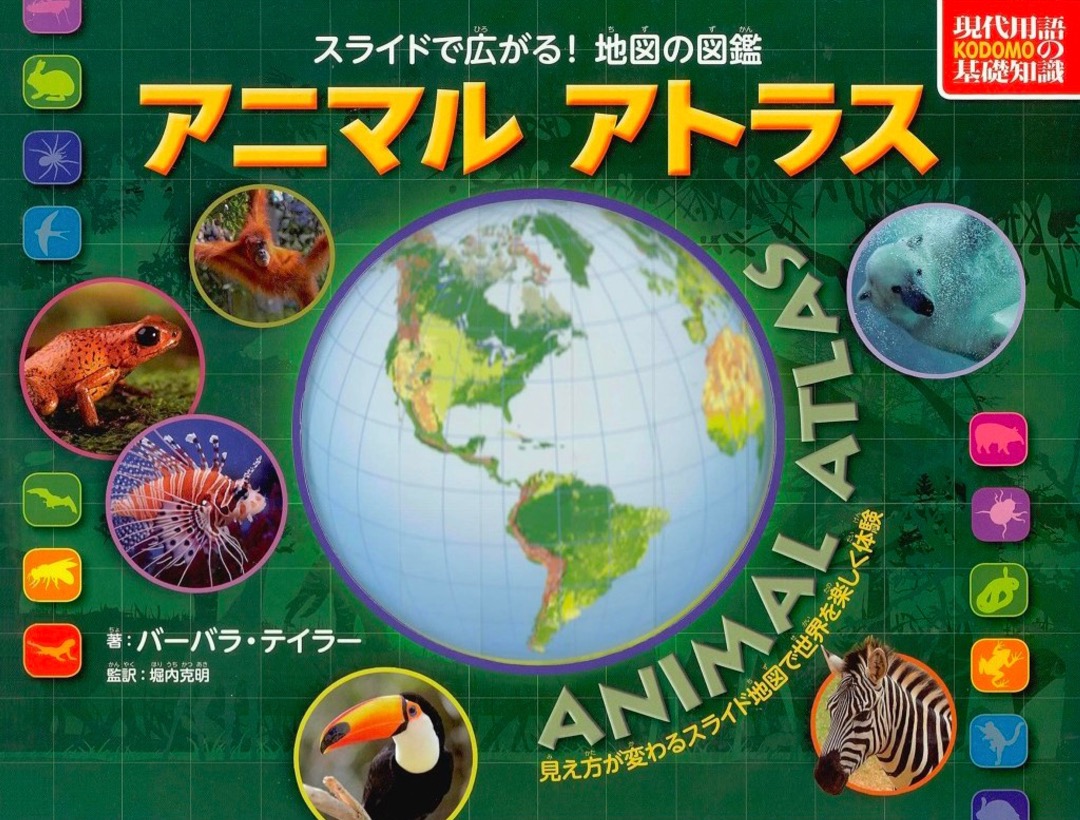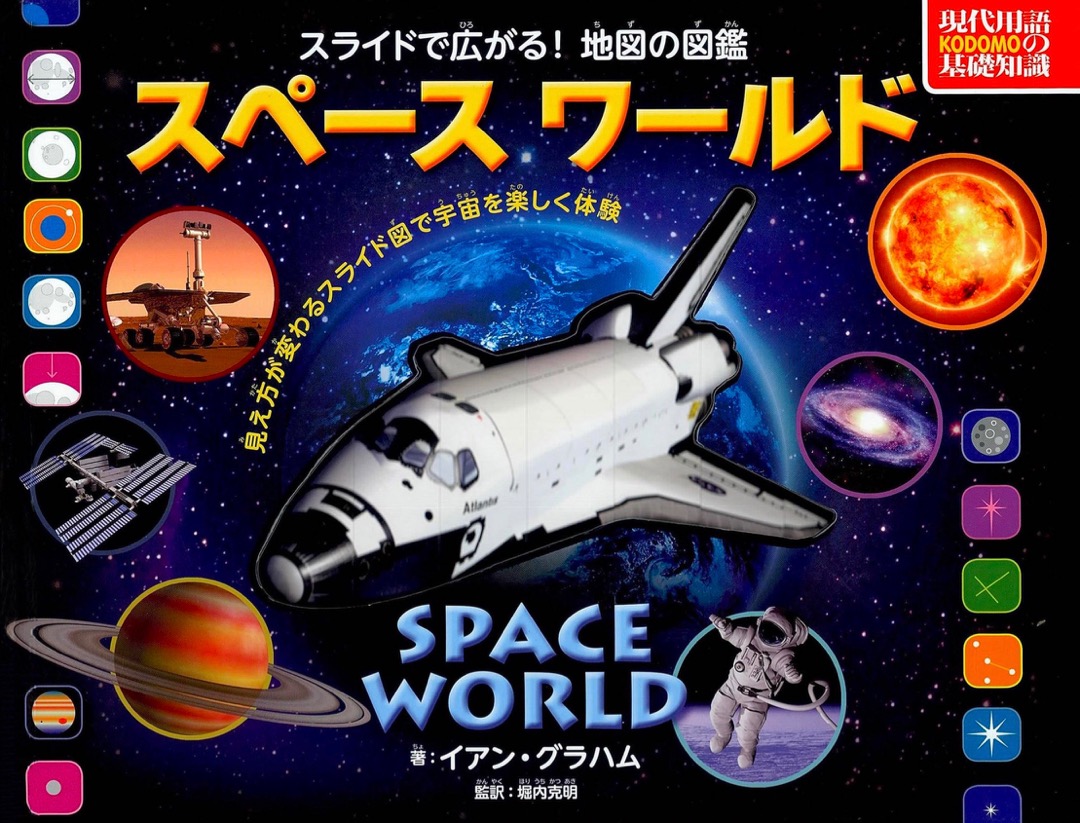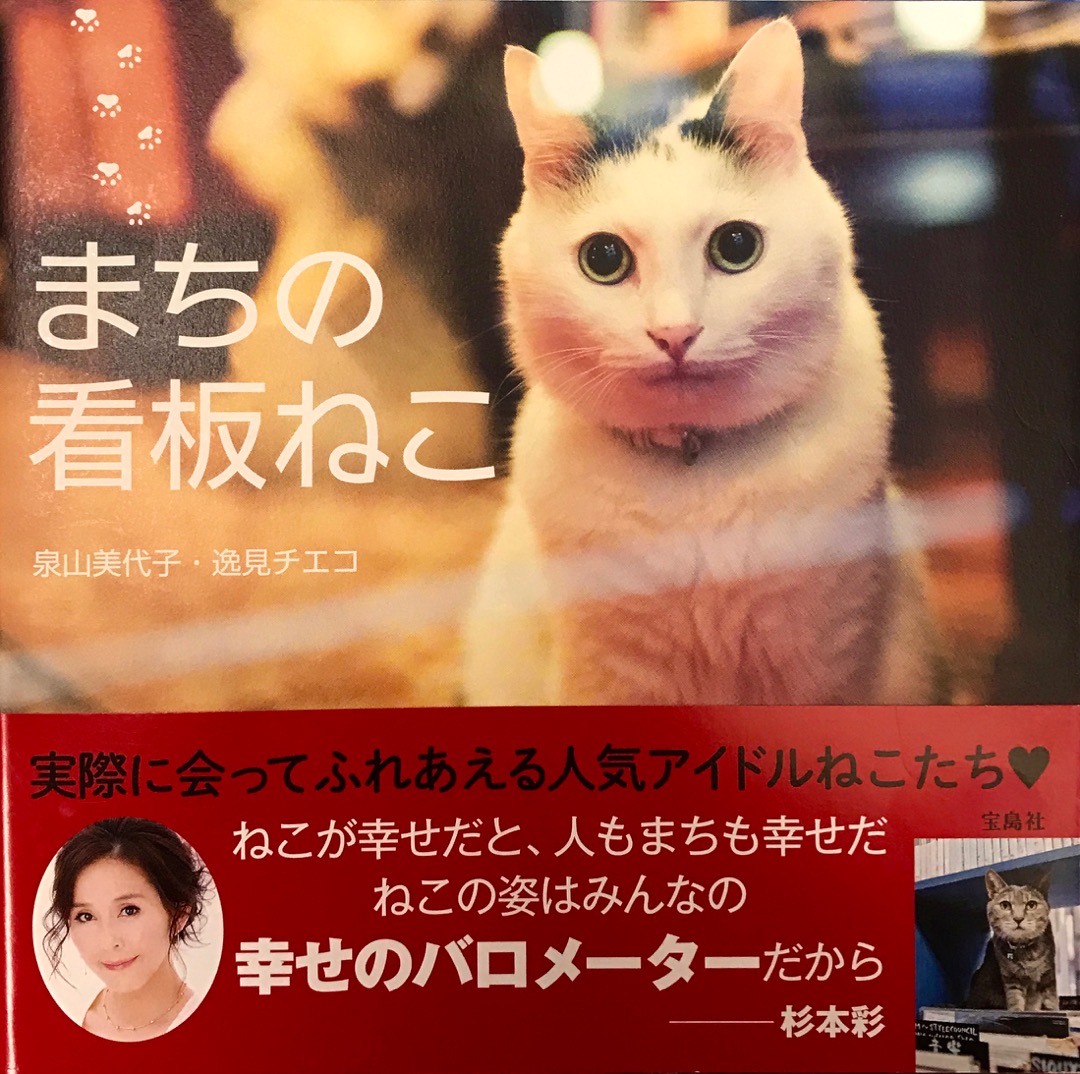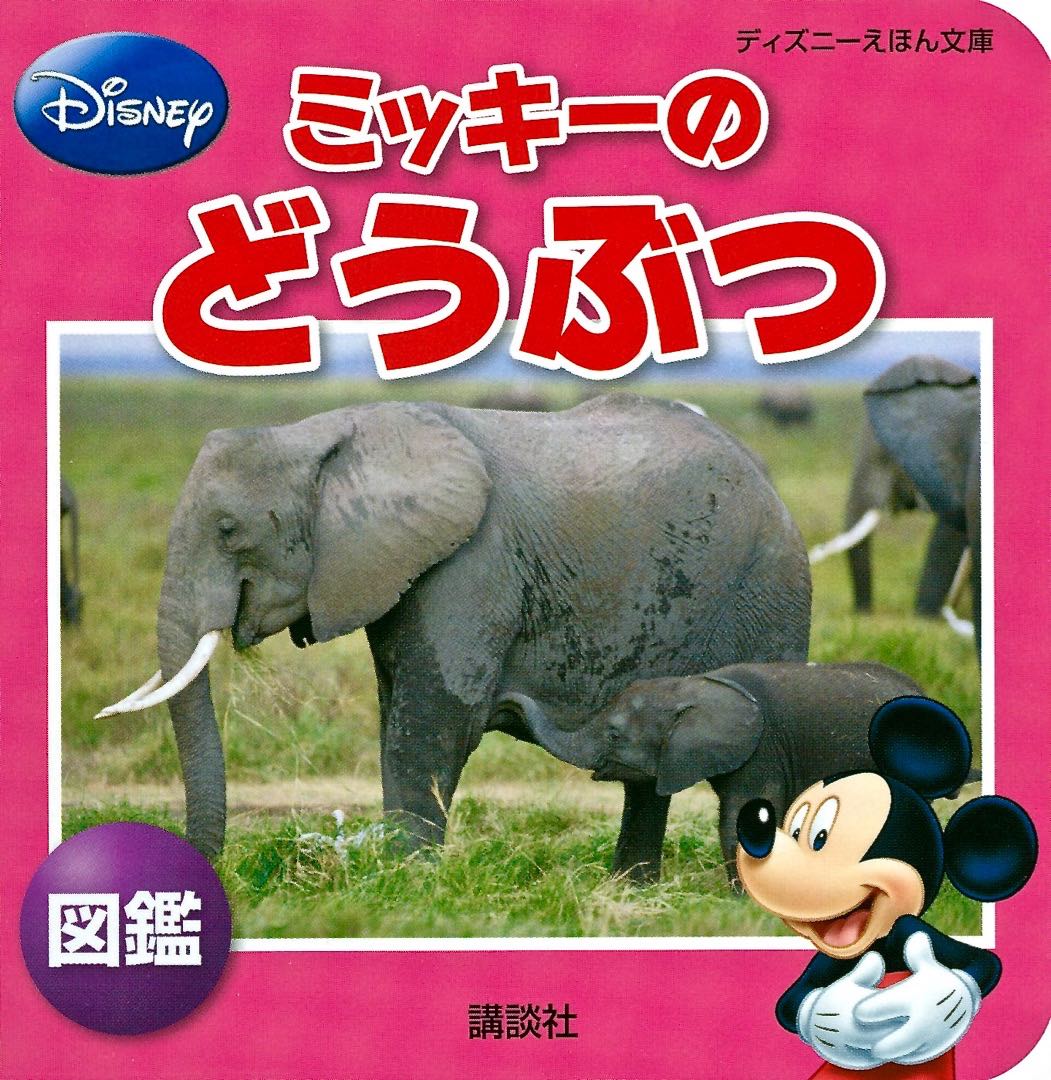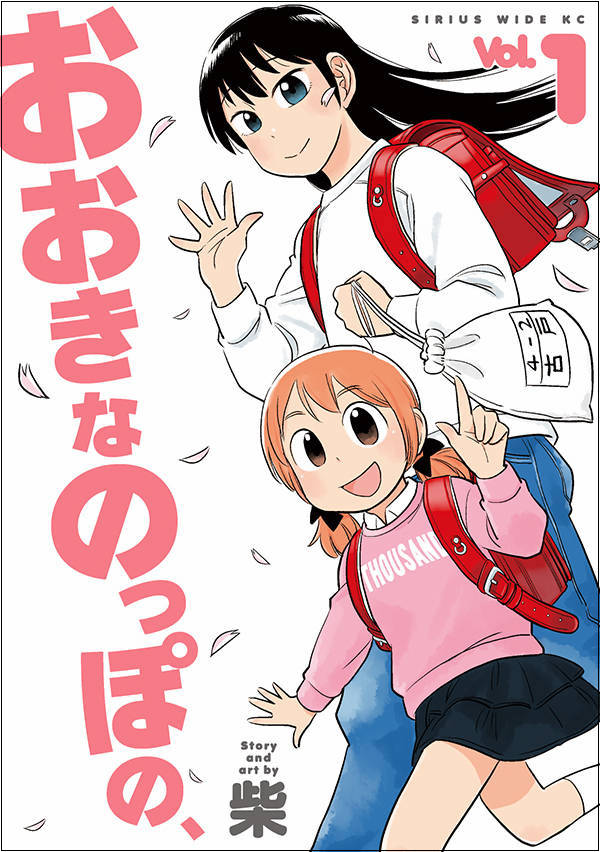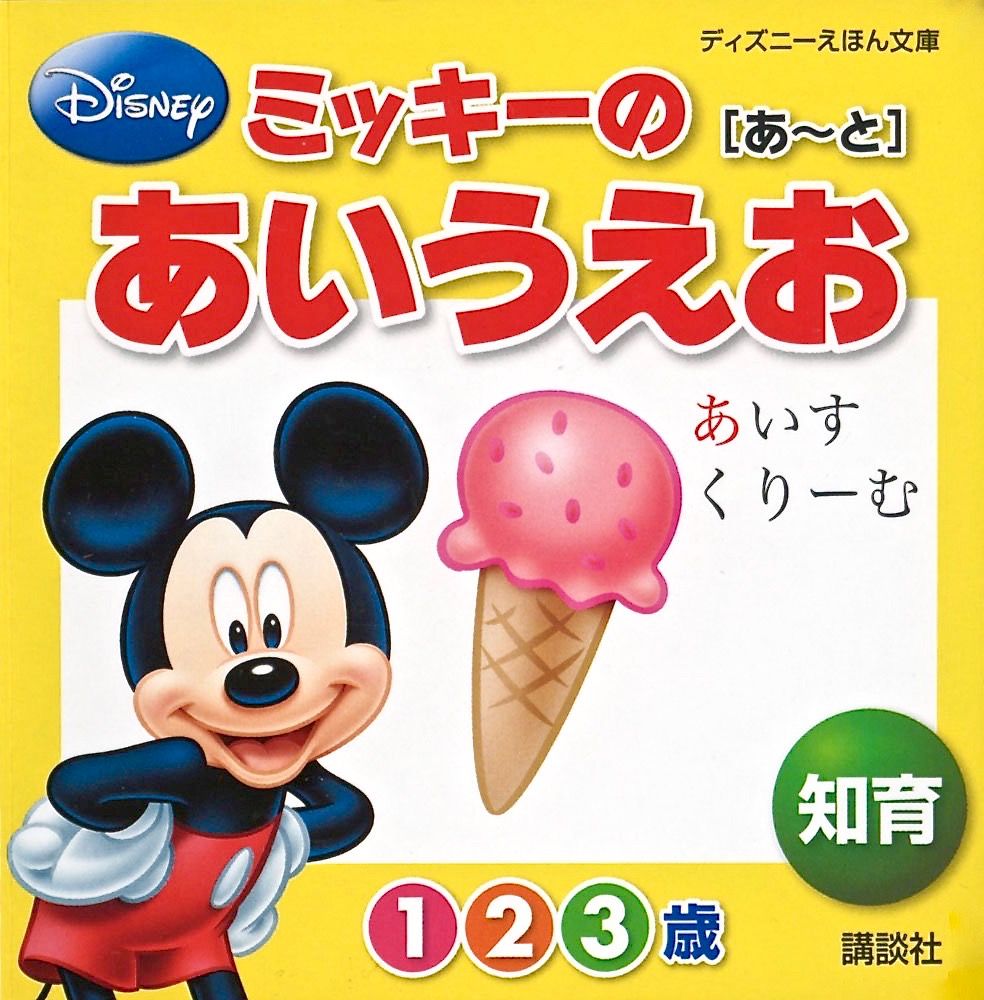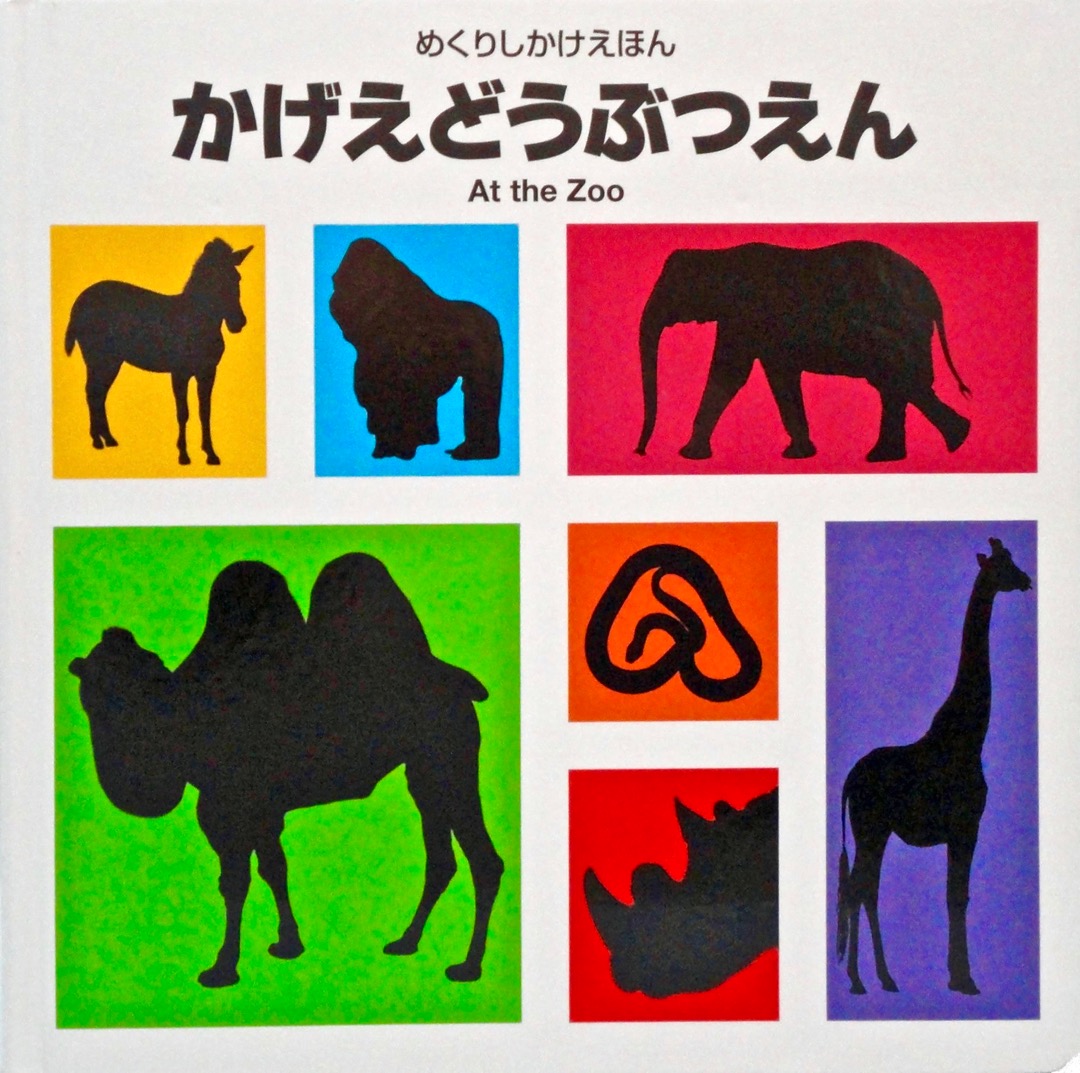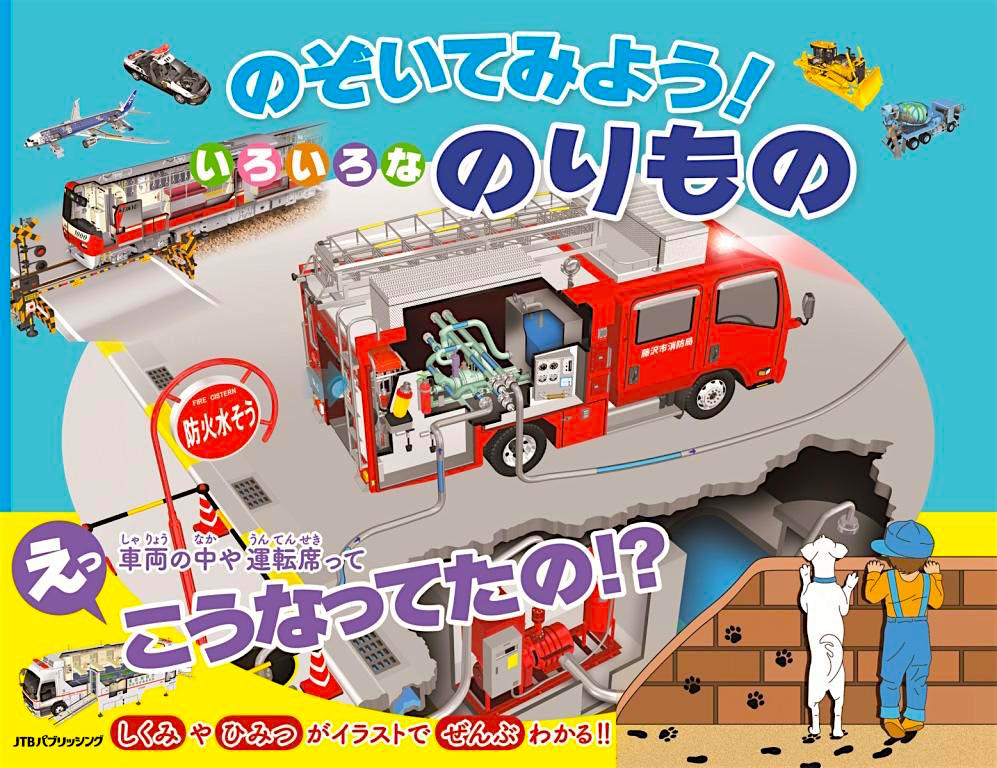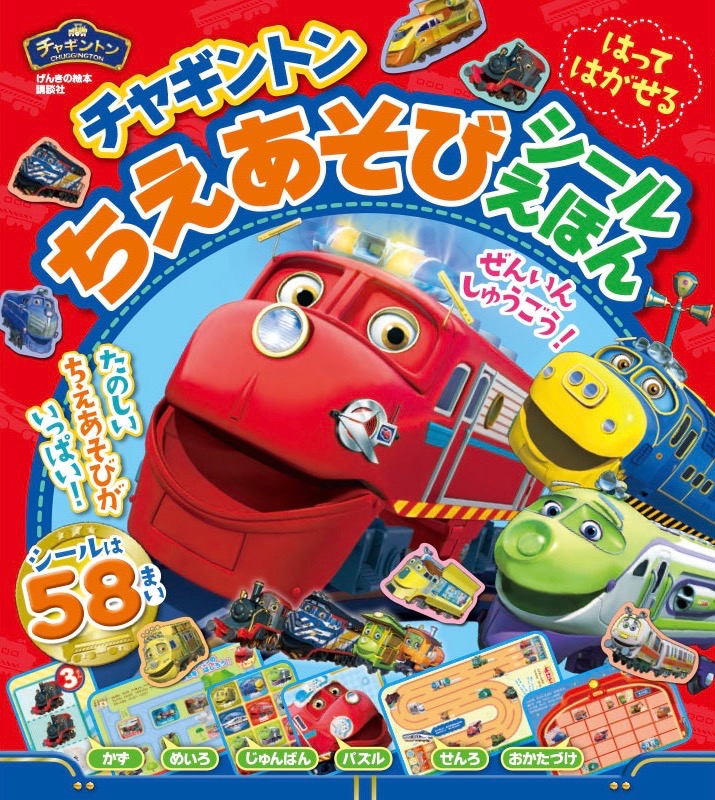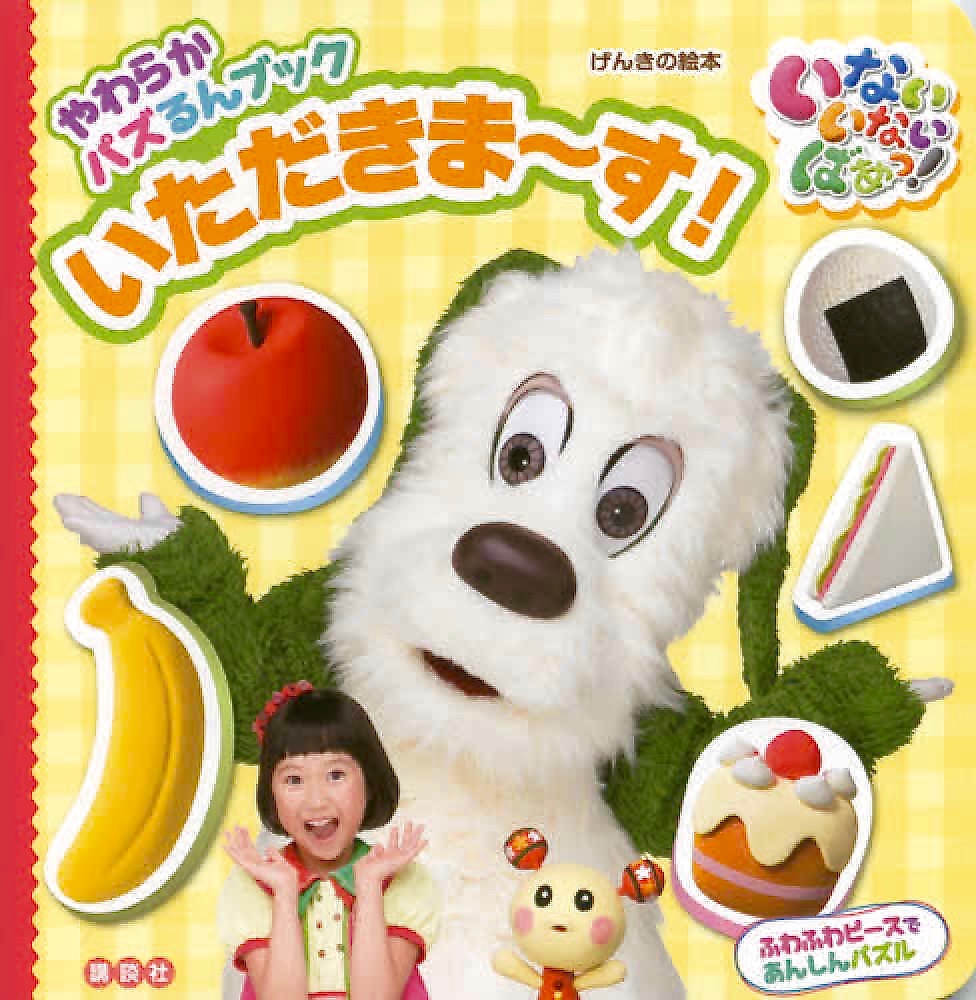
絵本  さとうゆたか  2014年8月22日(金) 7:31
書名:アントンせんせい
著者:西村敏雄
発行:講談社
同じ出版社の本  さとうゆたか  2014年8月22日(金) 7:34 [修正]
書名:ギャロップ!!
著者:ルーファス・バトラー・セダー
翻訳:たに ゆき
発行:大日本絵画
おはなしの世界で!  さとうゆたか  2018年2月1日(木) 16:12
書名:まちがいさがし
著者:大河原一樹/幸池重季/大寺聡/なかさこかずひこ!
発行:高橋書店
音楽会のポスター  さとうゆたか  2018年1月19日(金) 10:40
ちょっと古いか…。
しかけ絵本  さとうゆたか  2016年10月7日(金) 16:57
書名:ABCのかくれんぼ
著者:
クリストファー・フランチェスチェッリ/ぶん
ペスキーモ/え みたかよこ/やく
発行:大日本絵画
同じシリーズ  さとうゆたか  2016年12月22日(木) 17:00 [修正]
書名:ひとりぼっちのおさかなくん
著者:トーマス・フリンタム、みた かよこ
発行:大日本絵画
これも…  さとうゆたか  2017年12月17日(日) 11:22 [修正]
書名:こうじしゃりょうのえほん
著者:クリストファー・フランチェスチェッリ、ペスキーモ
発行:大日本絵画
にじいろでんしゃ  さとうゆたか  2017年12月3日(日) 15:10
書名:はっしゃしまーす!
著者:間瀬なおかた・間瀬なおかた
発行:学研教育みらい
「ゃ」の文字に手が加えられていて、オリジナルのカタチではない。
なんで、平均的なカタチにしたがるのかな…。
ポスター  さとうゆたか  2017年11月16日(木) 16:02
インフルエンザ予防ポスター。
イベントのロゴ  さとうゆたか  2017年11月7日(火) 16:52
かんとうみんてつモバイルスタンプラリー。
CDえほん  さとうゆたか  2017年9月11日(月) 15:06
書名:ももたろう・したきりすずめ
著者:川内彩友美
発行:講談社
旅行の勧誘  さとうゆたか  2017年9月7日(木) 16:01
近所の駅に置かれていたチラシ。